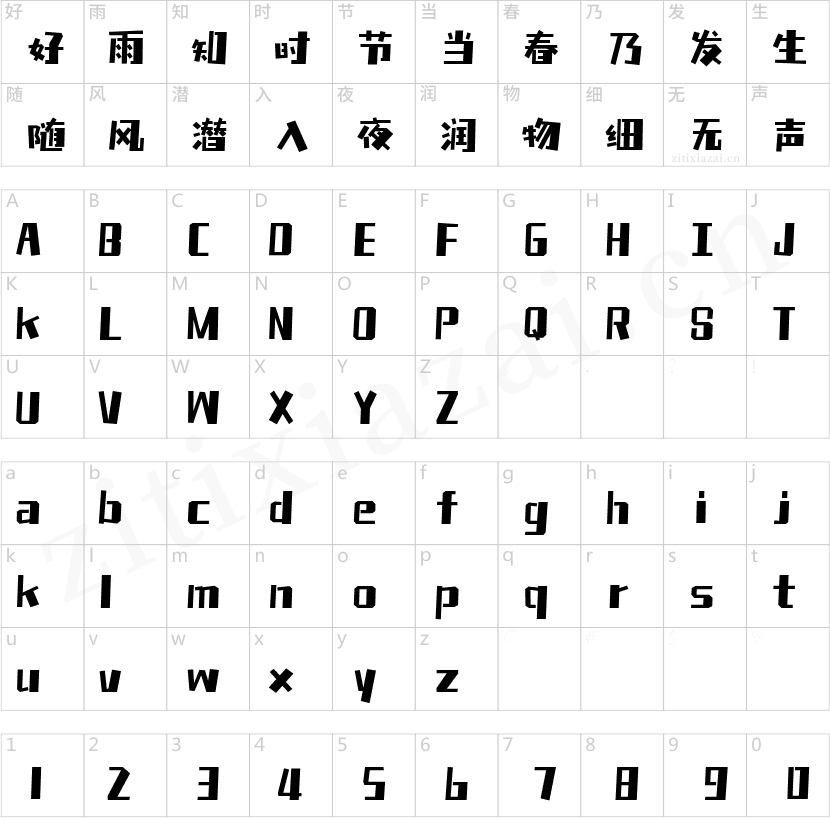
喵字冻柠体1.003
喵字冻柠体1.003,这款字体结构工整、笔画清晰,兼顾美观与易读性,适用于标题、正文、海报、包装、LOGO 等多种场景。字形优雅稳定,风格百搭耐看,适配日常排版与创意设计,让文字呈现更舒适、更具质感。喵字冻柠体1.003一笔一画,皆是细节,以均衡的比例、流畅的线条打造舒适视觉体验,字形端正大气,风格简约现代。无论是商业设计、品牌宣传还是日常排版,都能轻松驾驭,让文字更有格调与力量。喵字冻柠体1.003字体下载。